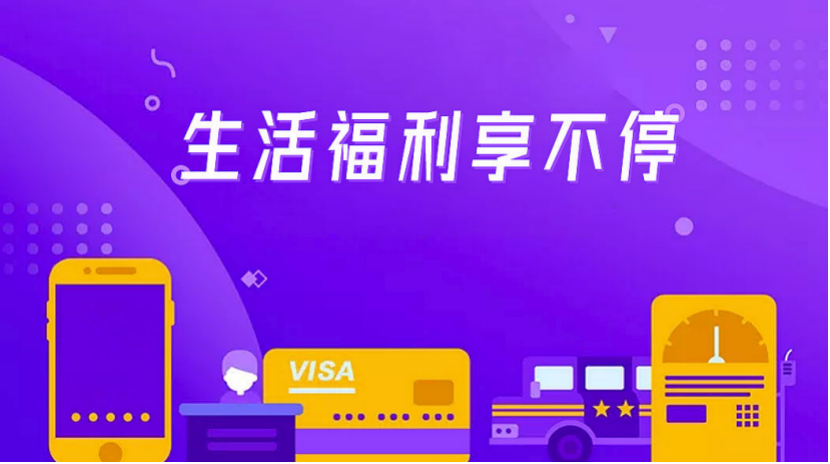
来自字体圈邹乐伟设计的一套免费商用的字体,这套字叫《字体圈欣意冠黑体》,欣意=心意。对于这套字体的发布,不希望只限于这是一套字体,我更想纪念一件事情,那就是今年的疫情。我想以我专业技能为抗疫发声,希望疫情能早点退去,早点让祖国,让世界恢复往日的繁华。这套字从开始设计到修改到最后开发,用了将近一年的时间(字形设计制作6个多月,后期修改+开发3个多月)。
全新3.0更新了:
部分字形
重新设计西文数字标点部分
添加3000+个繁体字符,现在字符数量是将近10000个了
还原字形默认大小
添加了生僻字“biang”
添加3000+个繁体字符